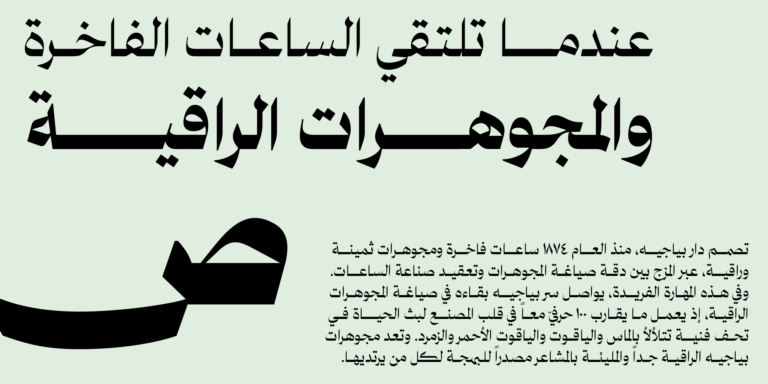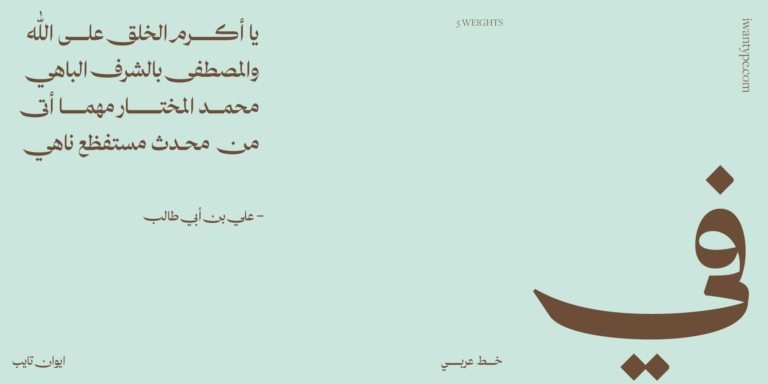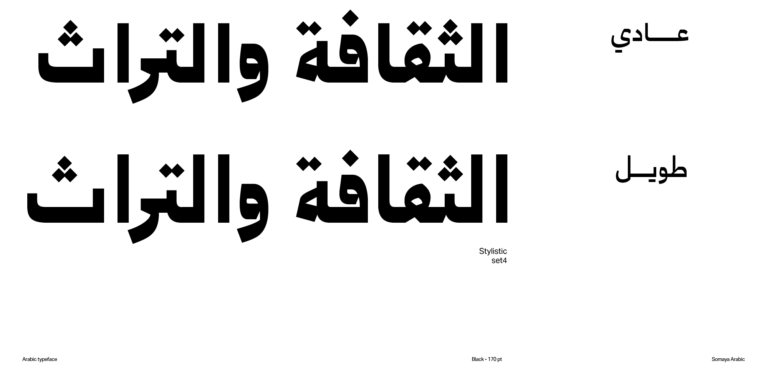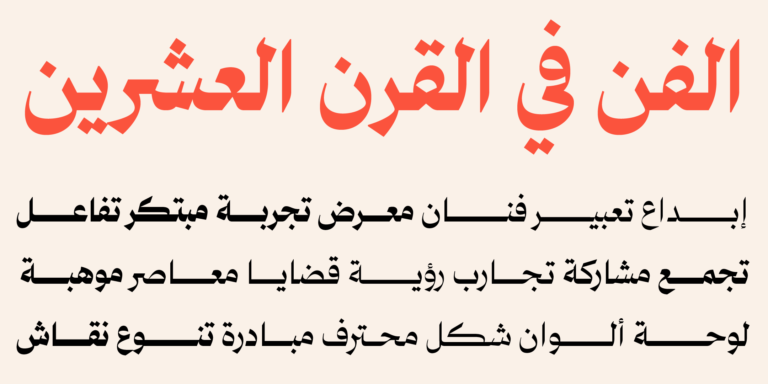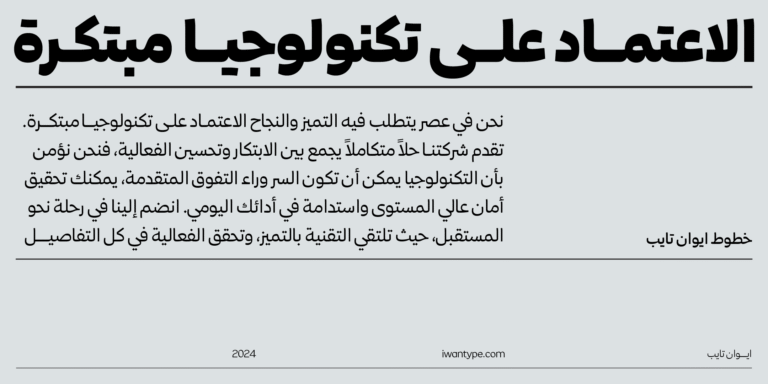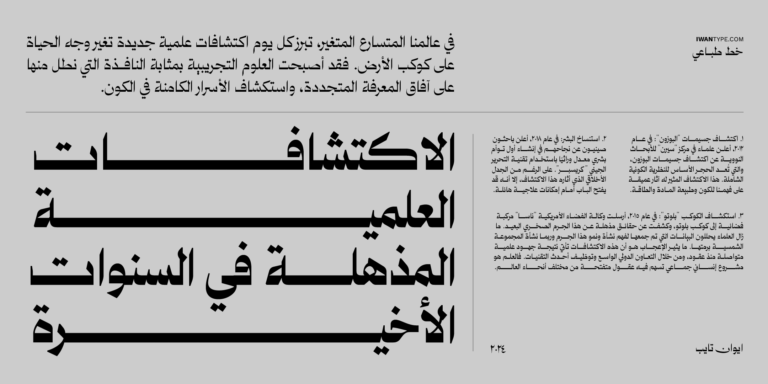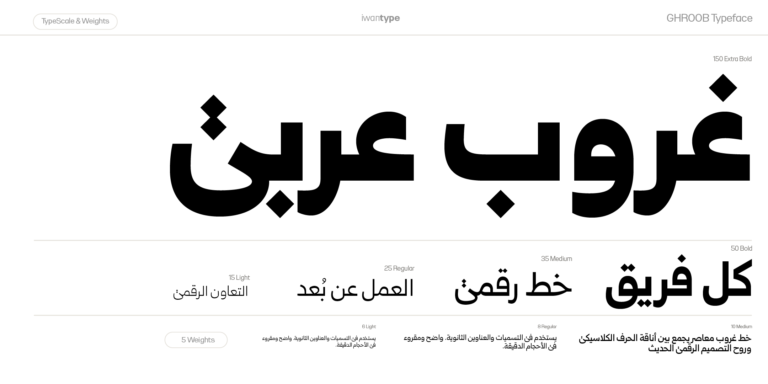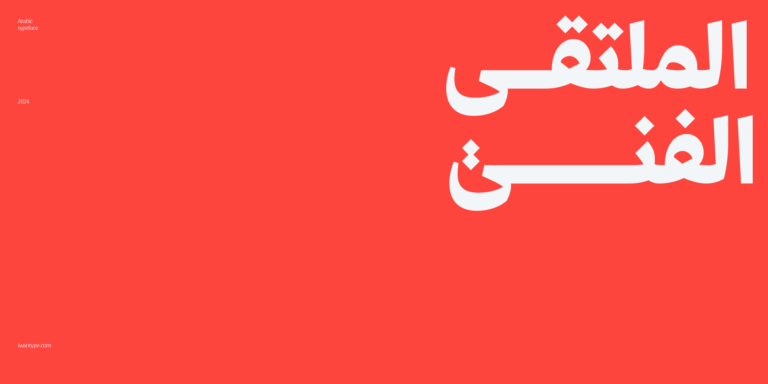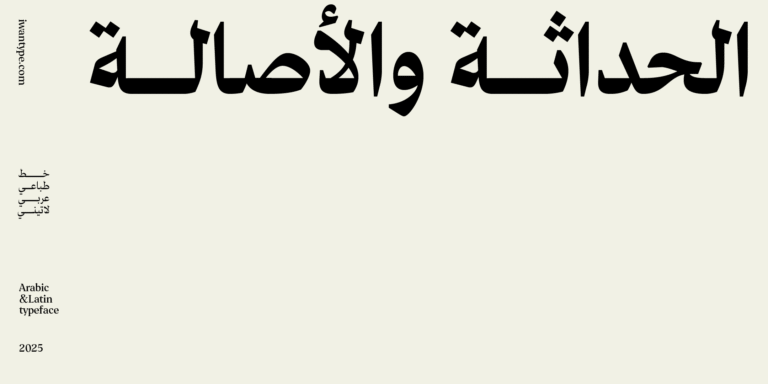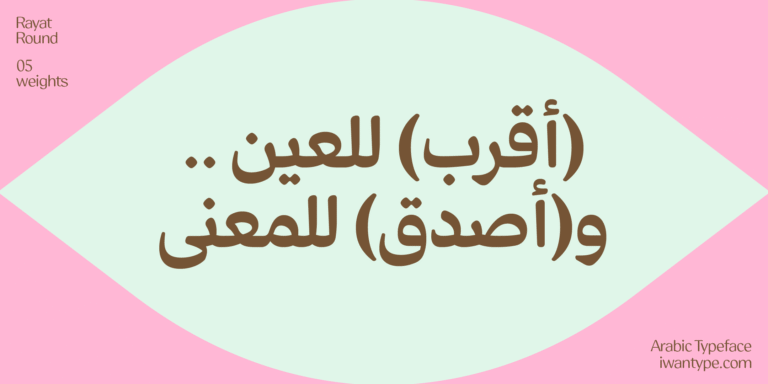
خطوط نسخ للعناوين — ١٥ خطًّا وأيّها لأيّ عنوان
العنوان ليس نصًّا مكبَّرًا. وخط النسخ الذي يريحك في فقرة من مئتي كلمة قد يبدو باهتًا حين تكتب به كلمتين بحجم ستّين بكسل، والعكس صحيح تمامًا. هذا الدليل يفصل بين الحالتين: ما الذي يجعل خطًّا نسخيًّا صالحًا للعنوان، ثم خمسة عشر خطًّا من كتالوج إيوان تايب مرتّبة بنوع العنوان لا بالذوق.
ما الذي يفصل خط العنوان عن خط النصّ؟
الجذر النسخي واحد في الحالتين — الأصل مشترك، والفرق في المعالجة. أربع خصائص تحسم الأمر:
التباين. الفرق بين سماكة الجذع الرأسي وسماكة الوصلة الأفقية. كلّما اتّسع هذا الفرق ازداد الخط أناقةً في المقاسات الكبيرة، وازداد هشاشةً في الصغيرة — لأن الوصلة الرفيعة أوّل ما يضعف أو يتكسّر. التباين العالي ليس عيبًا ولا ميزة في ذاته؛ هو التزام بمقاس معيّن.
التجويفات الداخلية. المساحات المحصورة داخل الحروف. اتّساعها يجعل الحرف مقروءًا صغيرًا؛ وضيقها يمنح الكلمة كتلةً وحضورًا من بعيد — دون أن يحسّن التمييز تلقائيًّا، فقد ينسدّ الشكل في الأحجام الصغيرة والمسافات البعيدة. وهذا ما يفسّر أن خطًّا «قويًّا» في اللافتة قد ينسدّ في الفقرة.
الامتدادات الأفقية. أحرف بديلة يمتدّ رسمها أفقيًّا داخل جسم الحرف نفسه — تُعرف بـالأحرف المرسلة، وتُفعَّل قصدًا حيث تريدها، لا تُضاف آليًّا كمدّة بين الحروف. الامتداد يمنح الكلمة اتّساعًا وأناقة، لكنه يطلب عرضًا حقيقيًّا على الصفحة، ويصبح عبئًا في العمود الضيّق.
سُلّم الأوزان. العنوان الواحد نادرًا ما يكفي. تحتاج عادةً إلى ثلاث درجات على الأقل: رئيسي وفرعي وتمهيدي. والخط ذو السبعة أوزان يمنحك هرمًا كاملًا من عائلة واحدة، بدل أن تستعير الدرجات من خط آخر.
أوّلًا: حضور يُرى من آخر الشارع
هذه خطوط مبنيّة على الحضور. تجويفاتها مضبوطة على الكتلة لا على الوضوح الفردي للحرف، فتعمل حيث تكون المسافة بعيدة أو الزمن قصيرًا.
عناوين
اسمه وظيفته: نسب رأسية ممتدة وتباعد بيني محكم من تقاليد خطوط الصحف والإعلانات — أقصى كثافة بصرية داخل المساحة المتاحة، بحضور أعلى في مساحة أقل. وأوزانه المتدرّجة تكفي لبناء هرم عناوين كامل من عائلة واحدة.
يتألّق في العناوين الصحفية، وبطاقات المحتوى على منصّات التواصل، والملصقات، وأغلفة الكتب. وإن احتجت متنًا طويلًا إلى جانبه فاقرنه بخط نصّي — فيكتمل النظام.
محارف
حضور جريء بأوزان ضخمة، بالعربية واللاتينية — ستة أوزان.
مساحته الطبيعية الإعلانات والملصقات الكبيرة والعناوين التي يجب أن تُرى قبل أن تُقرأ — وقليل من الخطوط يفعل ذلك بقوّته.
رايات
نسخ حديث ببنية قوية وزوايا حادّة تمنحه طابعًا جريئًا. تجويفاته الداخلية واسعة، فيحتفظ الحرف بوضوحه وراحته البصرية خاصة في الأحجام الكبيرة، ويدعم العربية واللاتينية معًا. ومن ميزاته الأحرف المرسلة والنقاط البديلة وياء بنزول أقل تشدّ انتظام السطر.
للعناوين البارزة والعلامات التجارية التي تريد طابعًا عصريًّا قويًّا.
سمية
نسخ عربي حديث يمزج بين التقليدي والحديث في تناغم — بخمسة أوزان.
للعناوين الجريئة والهويات الشبابية والثقافية المعاصرة.
ثانيًا: عناوين فاخرة عالية التباين
هنا تأتي الفخامة من الفرق بين الثخين والرفيع. وكلّها تعطي أفضل ما فيها في المقاسات الكبيرة — فهناك يظهر هذا الفرق، وهو مصدر جمالها.
فاطمة
تباين عالٍ ونسب مميّزة تفصله عن الخطوط التقليدية — وهي الصفة الحاكمة لاستخداماته — مع تراكيب ومجموعات أسلوبية، بخمسة أوزان.
لأغلفة المجلات والمحتوى التحريري الفاخر، وهويات العطور والتجميل، والدعوات الراقية. ملاحظة تنفيذية: في الطباعة على خامات خشنة أو التطريز أو القصّ بالليزر اختر وزنًا أثقل من العائلة نفسها.
سلمى
مستوحى من النسخ المسطري بتباين عالٍ ووصلات جديدة بين الحروف تصنع جمالية لافتة — بخمسة أوزان.
لأغلفة المجلات والعناوين الكبيرة، وهويات الأزياء والمشاريع العقارية، والشعارات النصّية.
آصال
يجمع التقليد والحداثة بأناقة على أساس من الخطوط الهندسية، مع حروف بديلة ومركّبة — بستة أوزان.
للعناوين التحريرية والهويات الثقافية والتراثية المعاصرة والتغليف الراقي.
واحة
نسخ بذاكرة الإعلان العربي القديم — مستوحى من أسلوب النسخ الإعلاني الذي زيّن منتجات السبعينات والثمانينات، يوازن بين النقاء الكلاسيكي والفخامة العصرية بخطوطه الممتدة وأناقته. عائلته سبعة أوزان بالعربية والإنجليزية، ومن ميزاته الأحرف المرسلة — امتدادات احتفالية تُفعَّل قصدًا حين تريدها، لا مظهره الافتراضي — وياء بنزول أقل تعزّز انتظام السطر.
للعلامات التجارية والعناوين التحريرية وتصميمات المنتجات الفاخرة.
ثالثًا: فخامة هادئة — حين لا تريد دراما
هوية للعناوين
فاخر هادئ يجمع الأناقة العصرية باللمسة الكلاسيكية: منحنيات تميل إلى التربيع ومساحات داخلية واسعة تمنحه وضوحًا استثنائيًّا — بالعربية واللاتينية.
للهويات الفاخرة الهادئة، والمؤسسات الثقافية، والمطبوعات والكتالوجات، والمحتوى ثنائي اللغة. هدوءه مقصود وهو ميزته.
رواسي للعناوين
حواف حادّة وتباين جذّاب يجمعان التصميم التقليدي والحديث بلمسة فاخرة، مع حروف مركّبة — بستة أوزان.
لأغلفة الكتب والمجلات والعناوين التحريرية وهويات المؤسسات العريقة.
رابعًا: عنوان بروح المخطوط
ديوان
طباعي عربي معاصر يمزج ببراعة بين أسلوب النسخ ولمسات أنيقة من الديواني والرقعة — بأوزان متدرّجة.